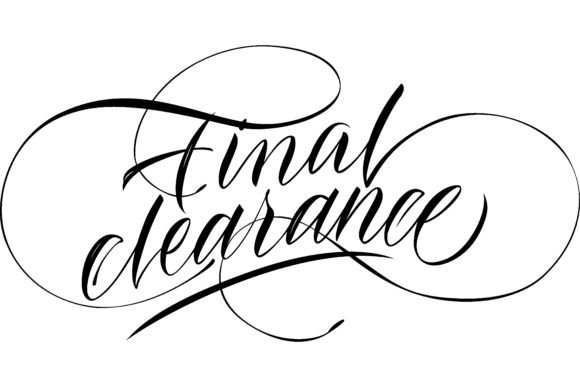
Justin Hailey Modern Font
Mencari elemen reka bentuk yang sesuai boleh menjadi mencabar, tetapi Justin Hailey Modern Font menawarkan koleksi luar biasa yang menaik taraf karya anda serta-merta.
Dicipta dengan ketepatan, Justin Hailey Modern Font menyediakan vektor yang bersih, tipografi yang licin dan lesen komersial untuk ketenangan fikiran.
Sama ada anda mencipta produk POD (Print on Demand), jemputan perkahwinan atau grafik media sosial, Justin Hailey Modern Font amat bersesuaian.